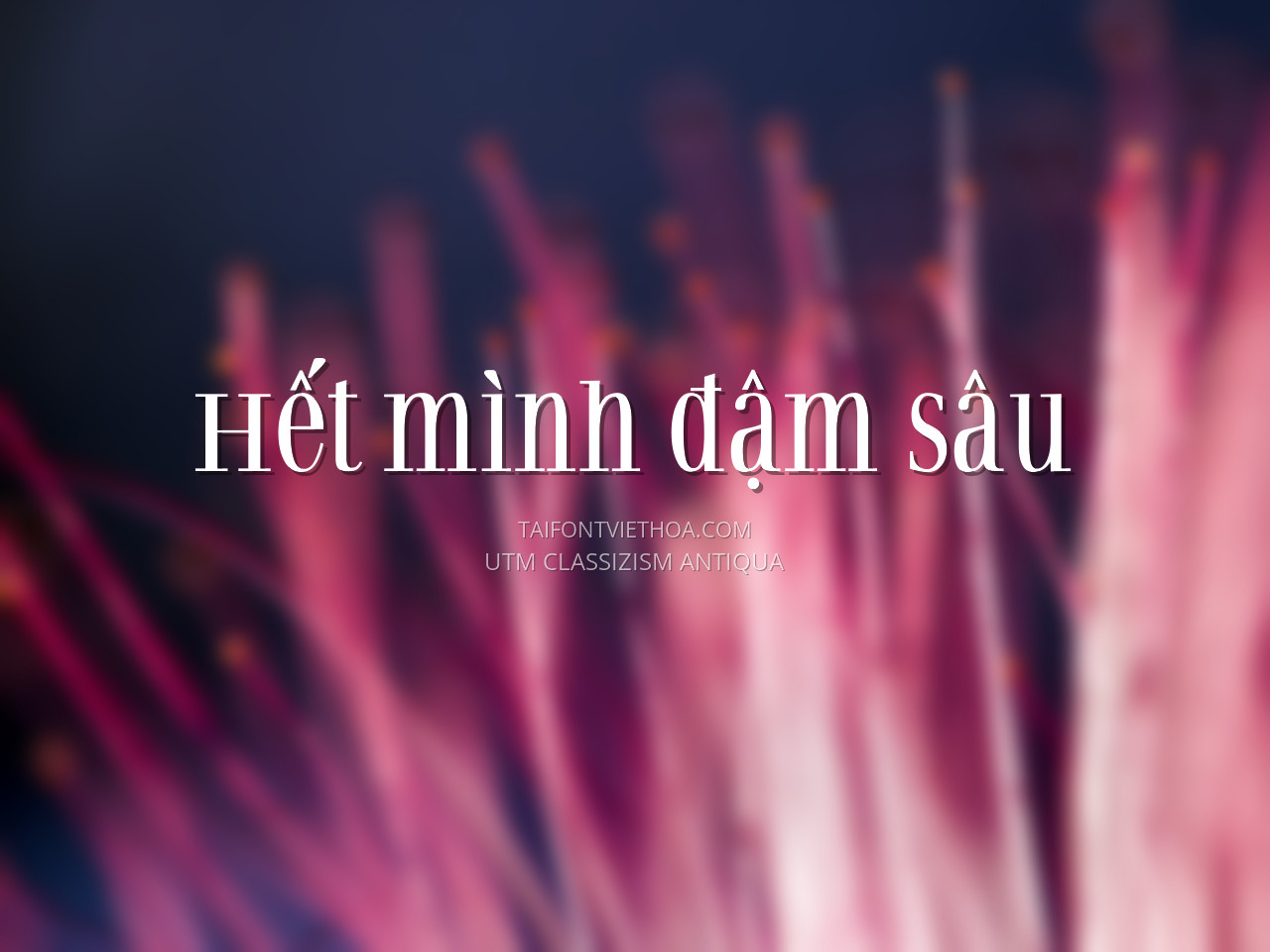
Giới thiệu về font UTM Classizism Antiqua
UTM Classizism Antiqua là phiên bản Việt hóa của font Classizism Antiqua – một kiểu chữ serif cổ điển, trang nhã và tinh tế, lấy cảm hứng từ phong cách typography cổ điển châu Âu. Font gốc nổi bật với các nét chữ có chân (serif) thanh mảnh, tỉ lệ cân đối và độ tương phản nhẹ nhàng, phù hợp cho các dự án thiết kế sang trọng và chuyên nghiệp. Phiên bản Việt hóa đã được hoàn thiện để hỗ trợ đầy đủ tiếng Việt cùng hơn 200 ngôn ngữ khác, mở rộng khả năng ứng dụng trong các dự án thiết kế đa dạng và đẳng cấp.
Đặc điểm thiết kế và ứng dụng của UTM Classizism Antiqua
UTM Classizism Antiqua sở hữu cấu trúc serif với các nét chân chữ thanh mảnh, độ tương phản vừa phải và thiết kế cân đối, tạo nên sự dễ đọc và trang nhã. Font có nhiều biến thể trọng lượng, giúp các nhà thiết kế linh hoạt sử dụng trong nhiều bối cảnh từ tiêu đề nổi bật đến nội dung chi tiết. Thiết kế font mang lại cảm giác chuyên nghiệp và sang trọng.
Font thích hợp sử dụng trong thiết kế sách, tạp chí, thiệp cưới, danh thiếp, bao bì sản phẩm cao cấp và các ấn phẩm thương hiệu sang trọng. Các ngành nghề phù hợp gồm: xuất bản, thời trang, tổ chức sự kiện, nghệ thuật, giáo dục và thiết kế nội thất.